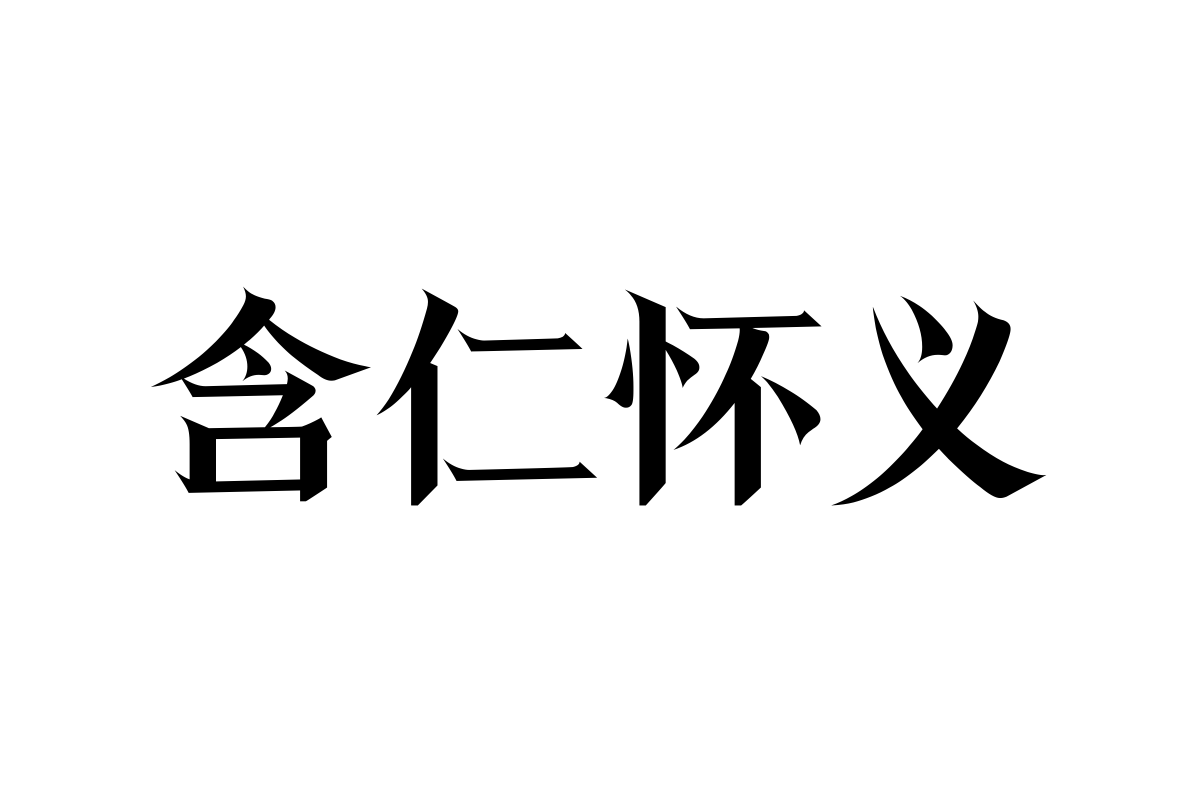
上首清雅宋体是一种中文字体,具有以下特点:
1. 字形结构:上首清雅宋体的字形结构简洁明了,笔画流畅自然,易于阅读和书写。
2. 笔画粗细:该字体的笔画粗细适中,既不过于粗犷也不过于纤细,适合各种场合使用。
3. 风格特点:上首清雅宋体具有一种清新、优雅的风格,给人一种宁静、舒适的视觉感受。
4. 适用范围:该字体适用于各种印刷品,如书籍、报纸、杂志、广告等,也适用于网页设计、电子屏幕显示等。